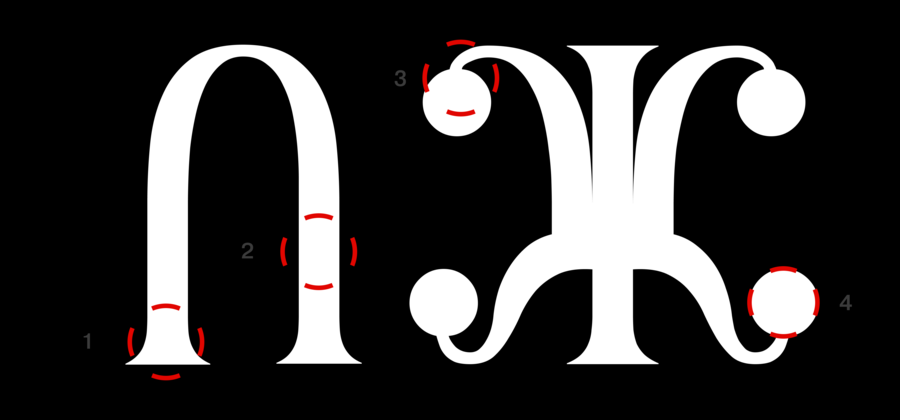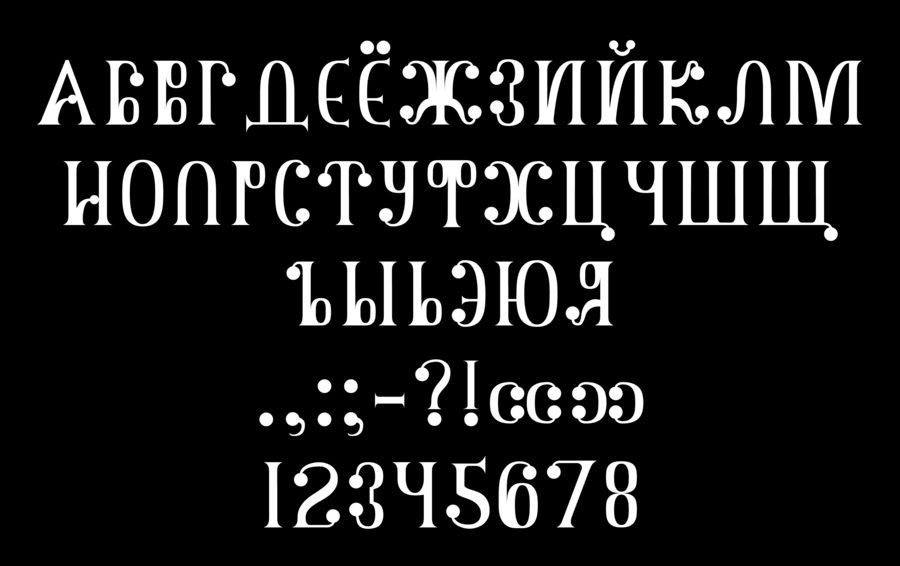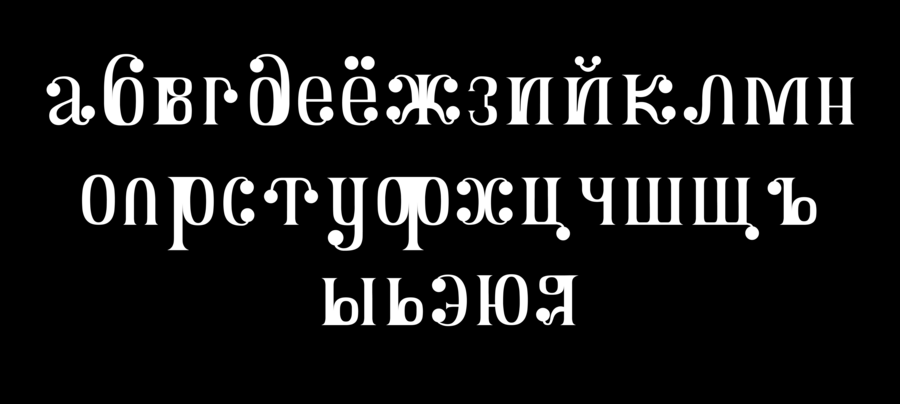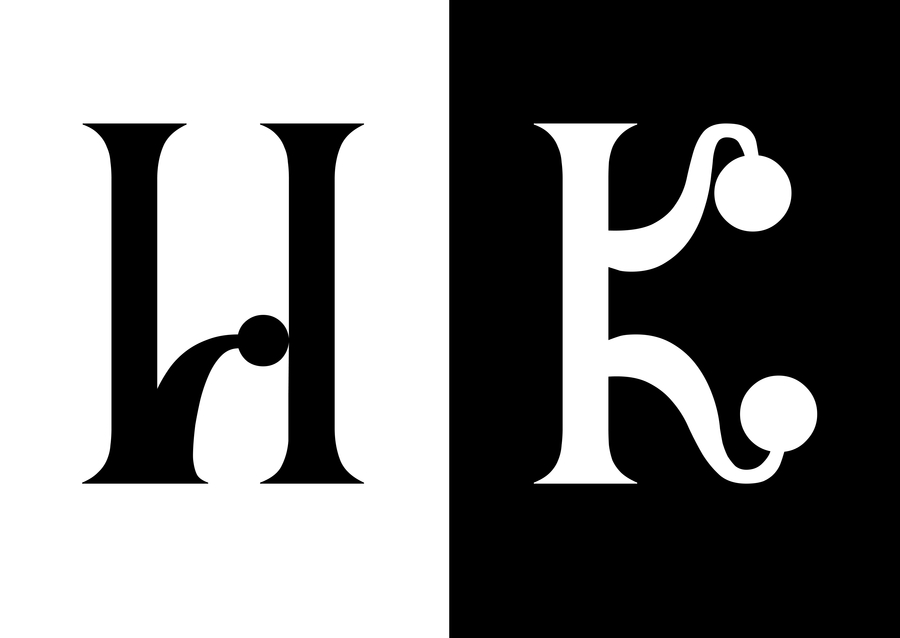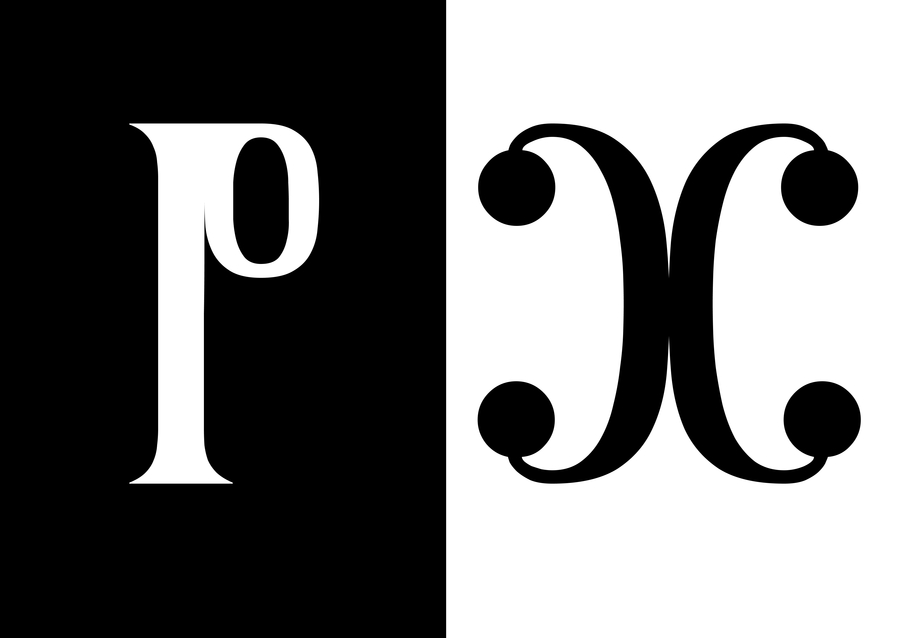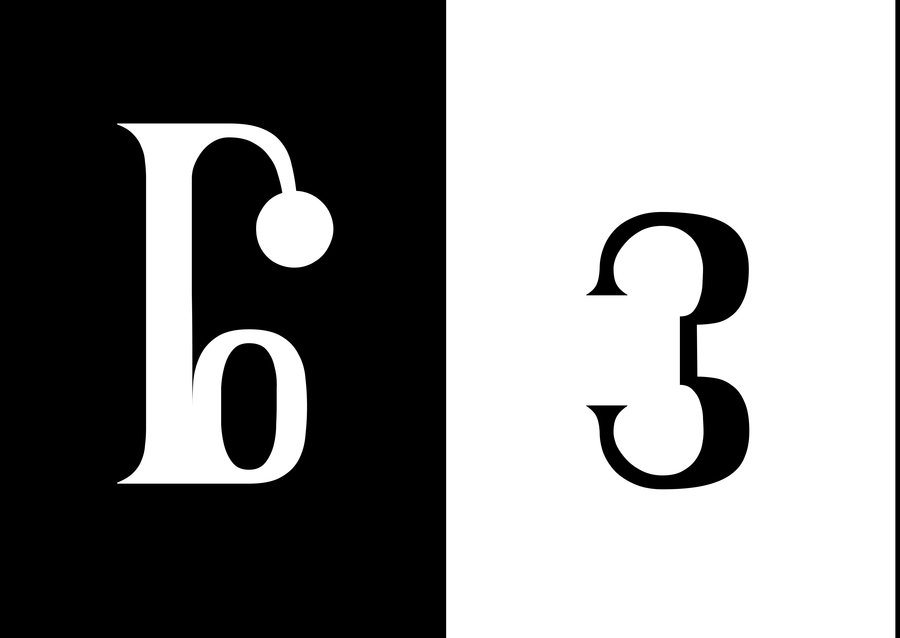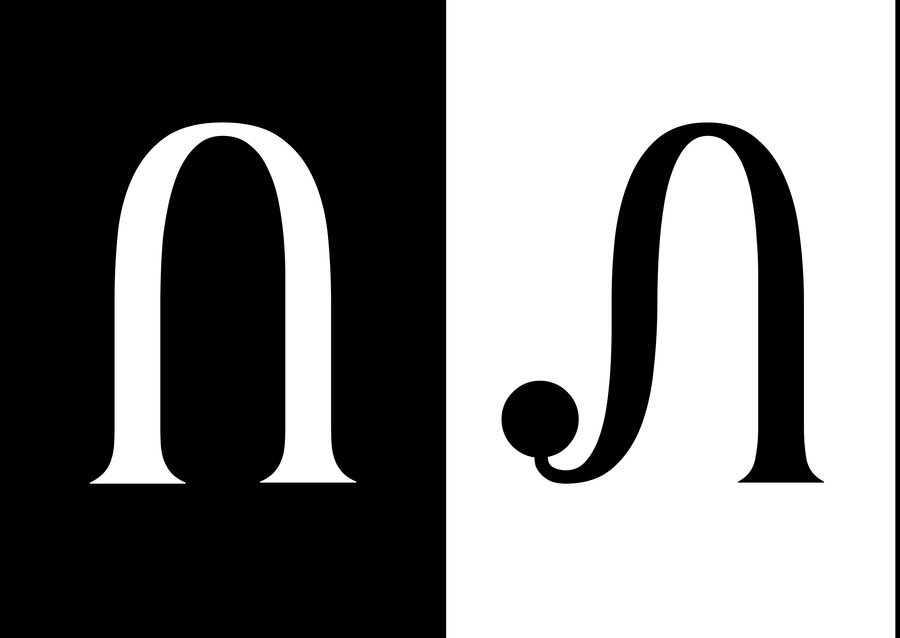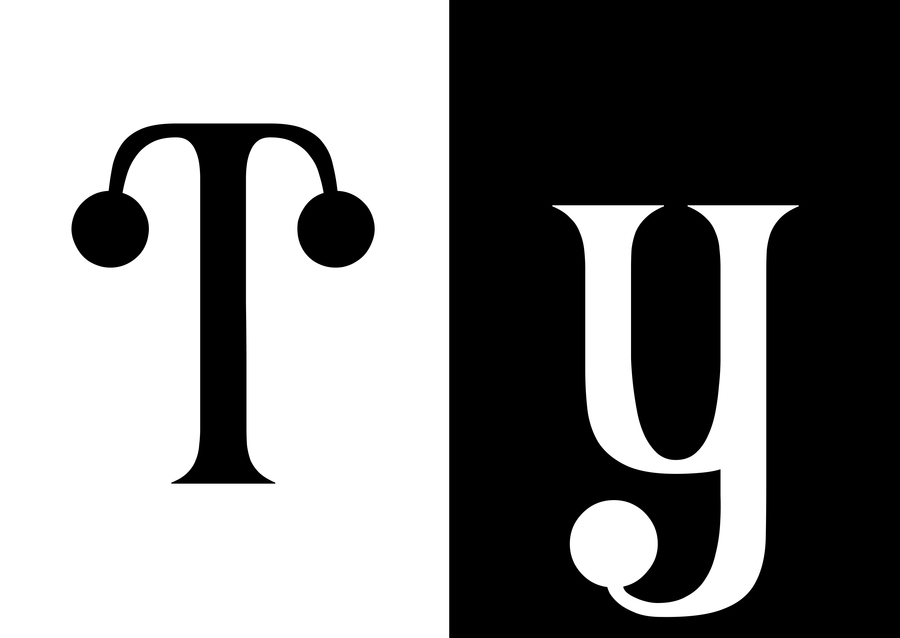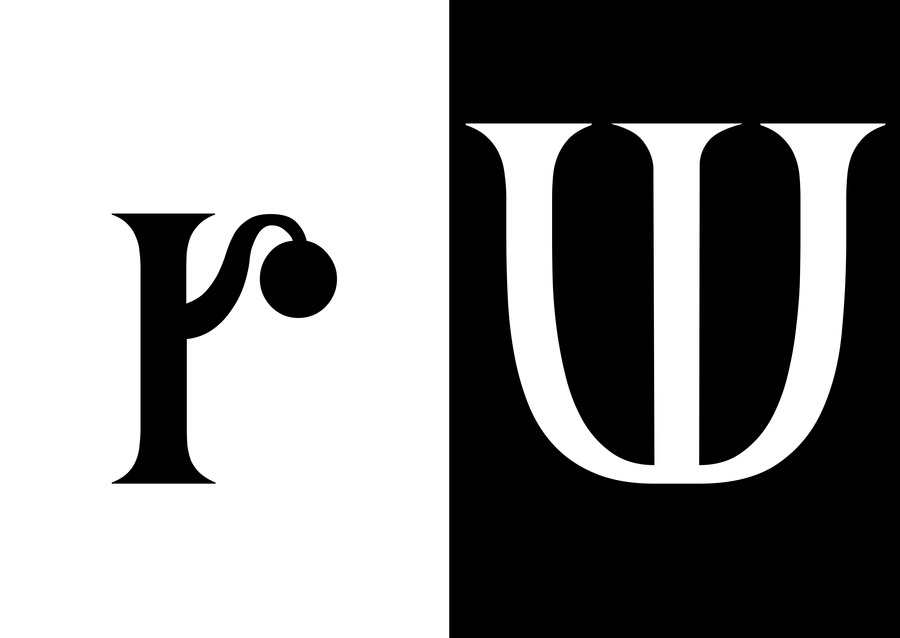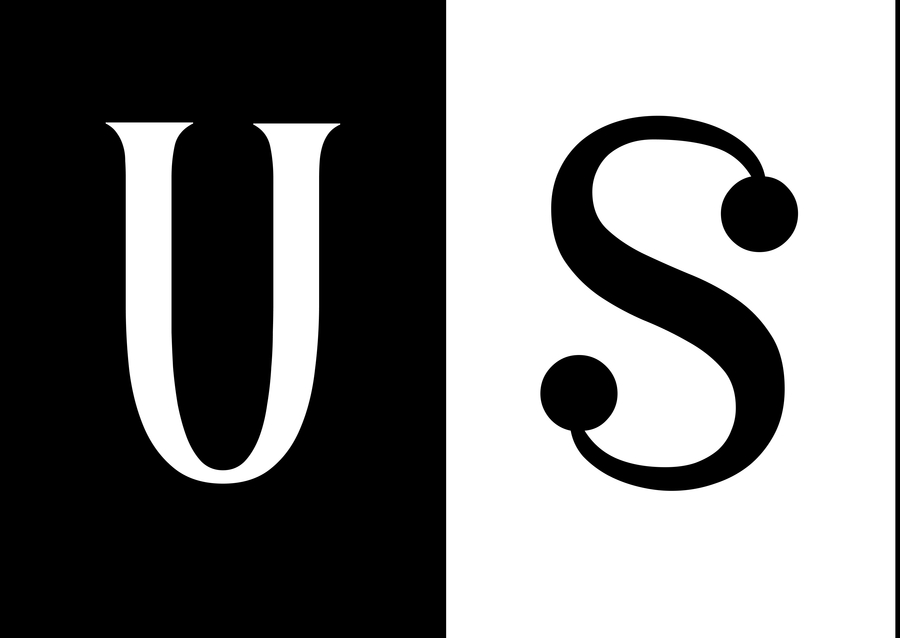
Шрифт Clownly
Шрифт вдохновлён цирковой эстетикой и деталями костюма. В основе жёсткий контур и крупные каплевидные акценты, которые дают ритм и сразу создают узнаваемый характер.
1—клиновидные завершения штрихов; 2 — жёсткий несущий каркас; 3 — контраст массы и пустоты; 4 — крупные каплевидные элементы.
Кириллица прописные
Кириллица строчные
Латиница прописные
Латиница строчные